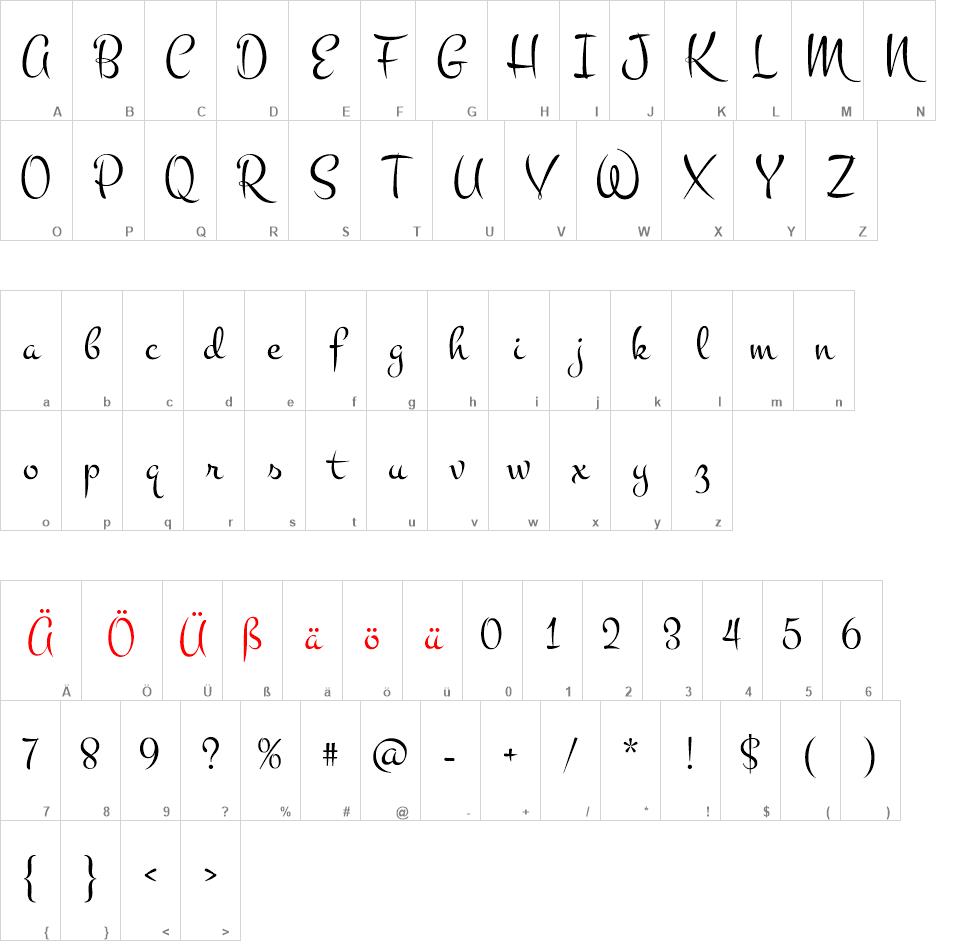
Montez Font
Montezuma ist eine Schrift, die von schönen Produktanzeigen aus den 1960er Jahren inspiriert wurde. Die weitreichenden Striche vermitteln Geschmack und Eleganz, ideal für die Verwendung eines kleinen Dramas, einer "Lebensfreude" oder eines Bildes, das die Freude am Leben erfordert. Die besten Einstellungen für eine bessere Lesbarkeit sind mittlere und große Textgrößen.